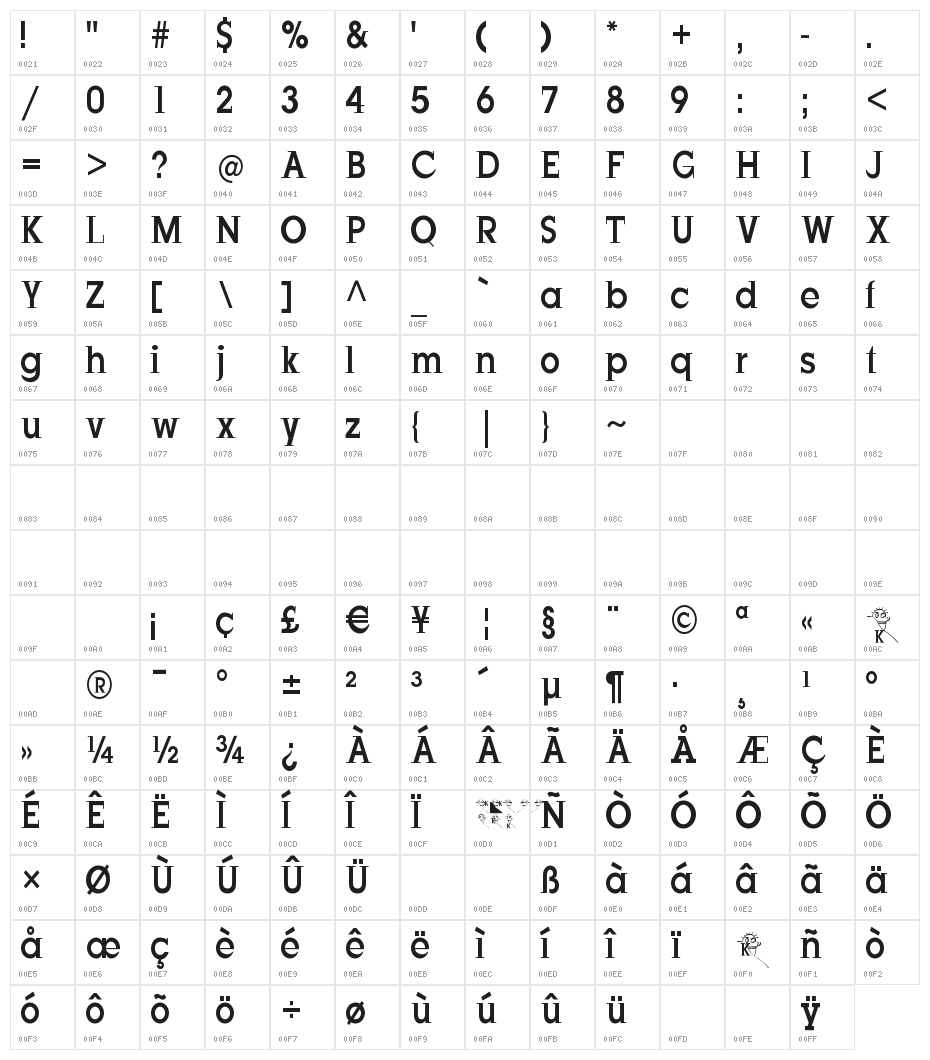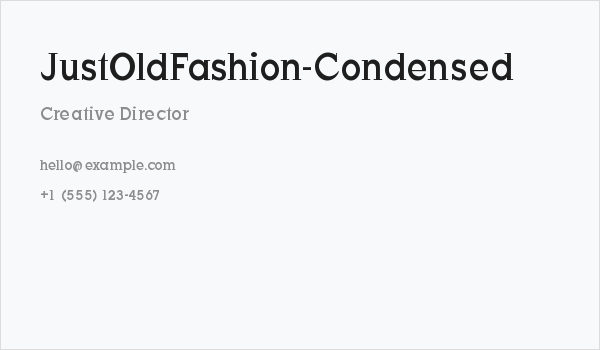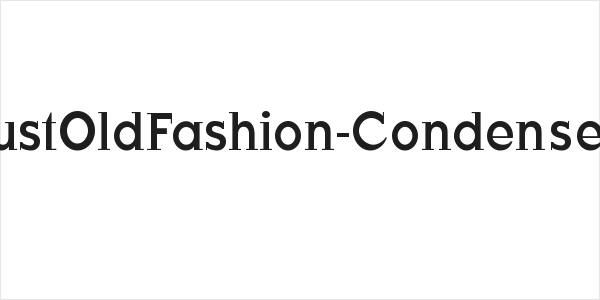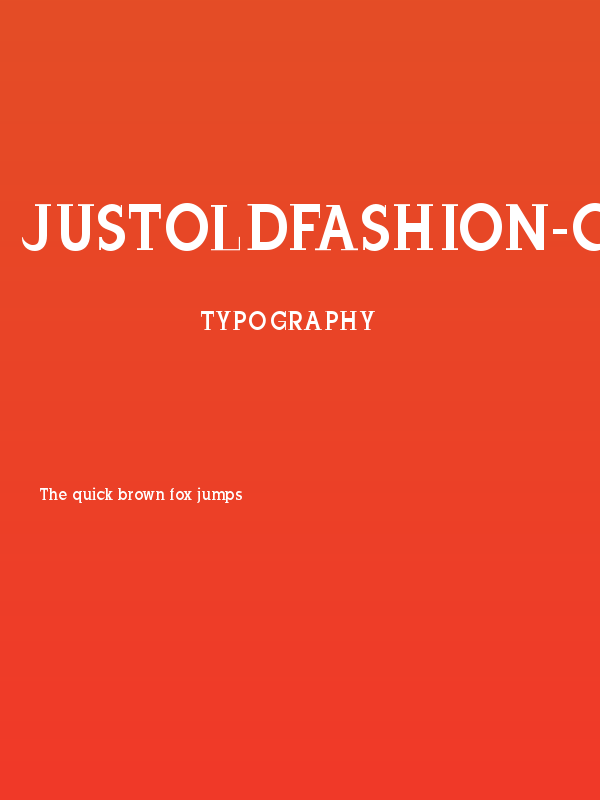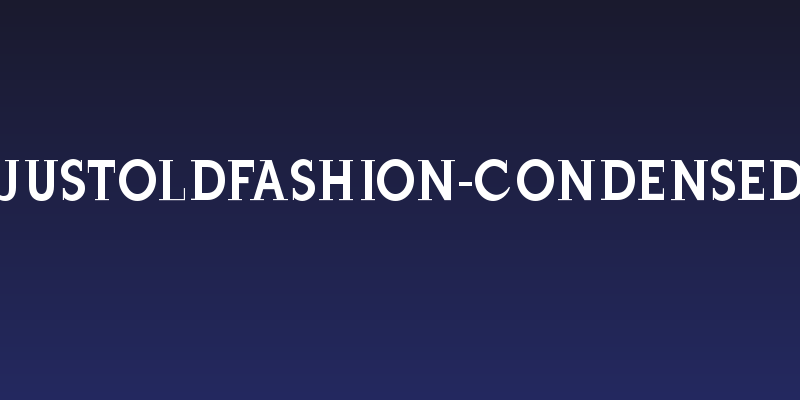
JustOldFashion-Condensed Font
| Proiecte propuse | Ideal for editorial design, book covers, formal invitations, and branding projects that require a touch of sophistication. |